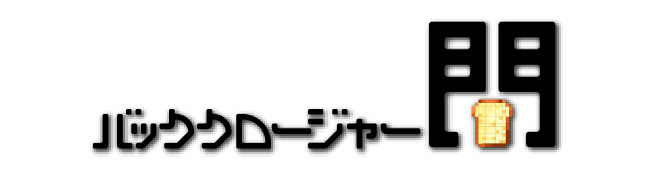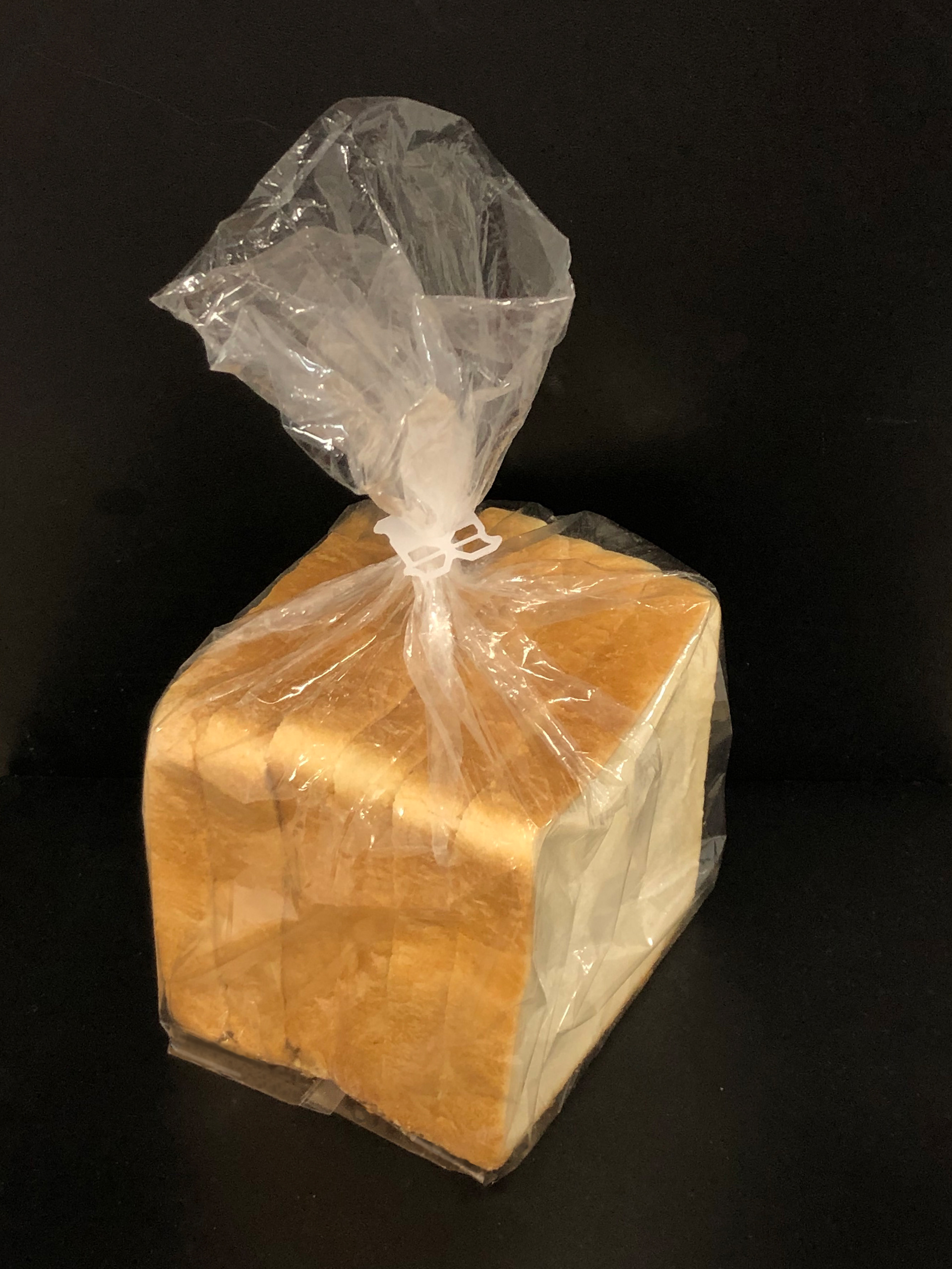
バッククロージャー門
食パンの袋をとめる道具である「バッククロージャー」を漢字の「門」に見立てたグッズです。
「バッククロージャー」と「門」という漢字の形状が似ていることか着想を得ました。食パンを乾燥や湿気から守る役割のバッククロージャーと、城や家を侵入や風から守る役割の門は見た目だけでなく役割まで類似しています。物の形が持つ意味を味わってほしいです。
アクリル板をレーザーカッターで切断して制作しました。「門」の字を抽象化し、バッククロージャーの形に寄せました。実際にバッククロージャーとして使用することも可能です。
また、「もんがまえ」を部首にもつ漢字によるパターンも制作しました。こちらはバッククロージャーとして使用することはできません。